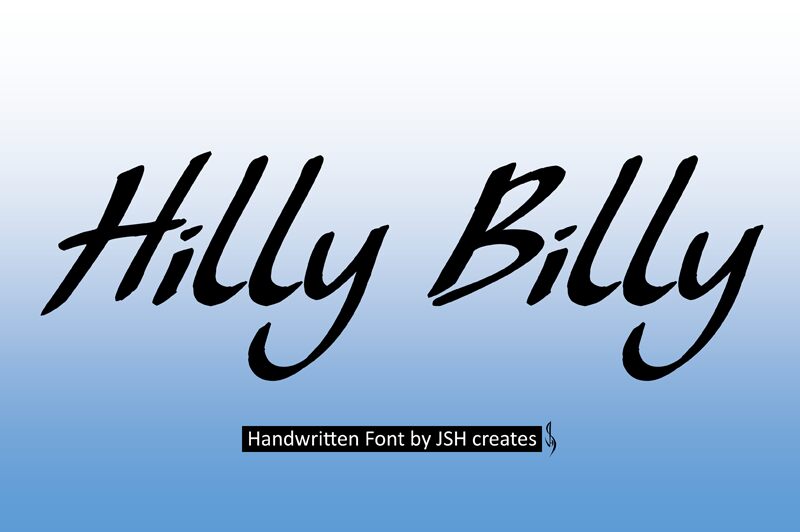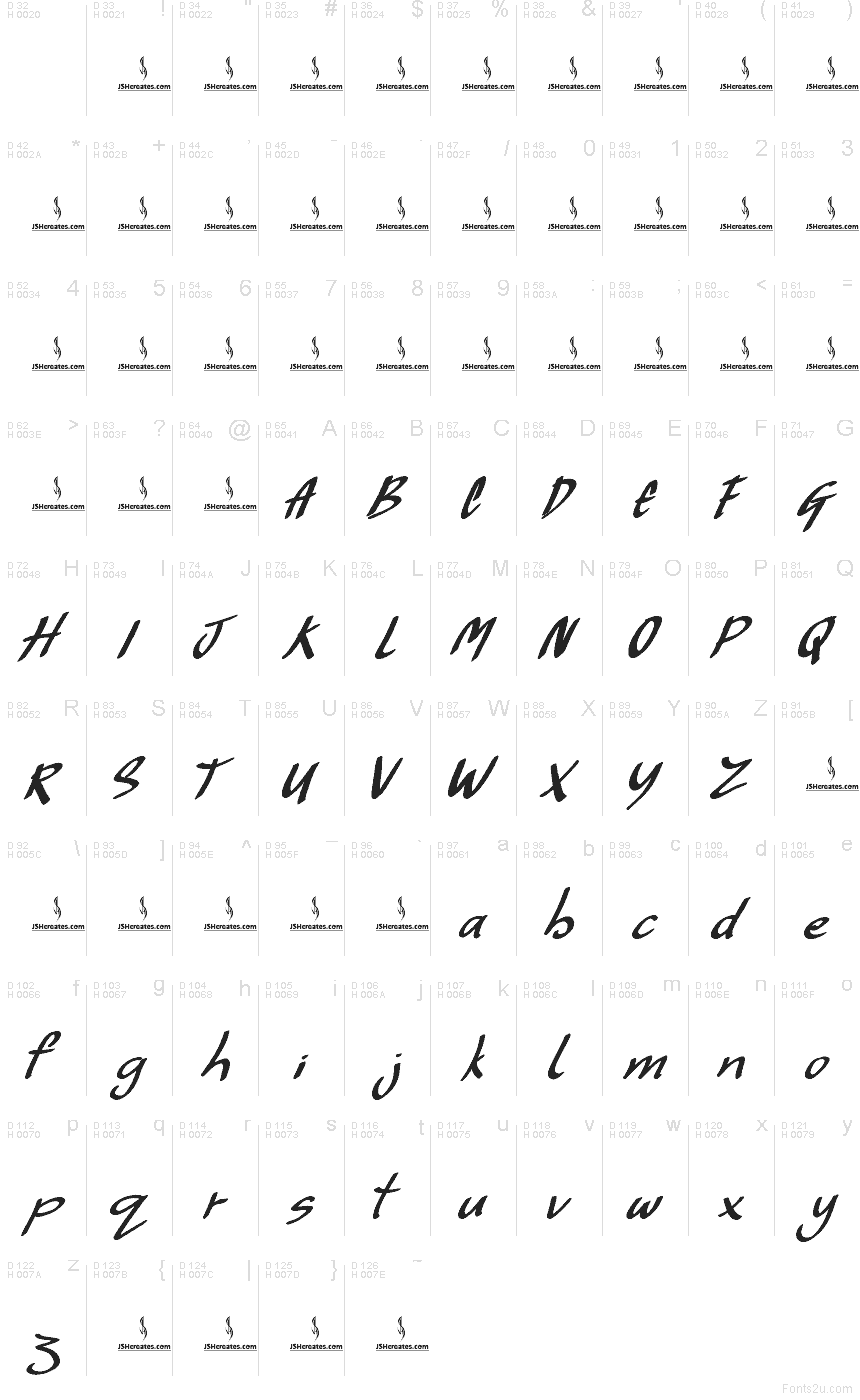
Hilly Billy
Hilly Billy от JSHcreates — это бесплатный рукописный шрифт в стиле быстрых мазков кистью. Буквы опираются на длинные, сужающиеся штрихи и легкое, связное движение, что придает шрифту свободный ритм в духе вывесок, нарисованных от руки, — скорее непринужденный, чем «вылизанный».
Он отлично подойдет для заголовков плакатов, брендинга кофеен, этикеток, цитат в социальных сетях и упаковки, где уместен бесплатный шрифт с легким, «домашним» характером. Используйте его для коротких заголовков, обложек или простых текстовых логотипов, когда хотите, чтобы буквы выглядели так, будто их набросали на ходу, — здесь всё решают резкие начальные штрихи и динамичные соединения.